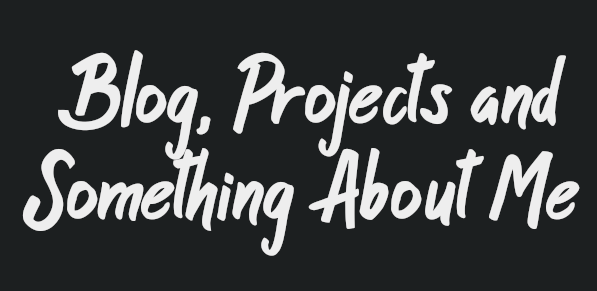
Çok araştırdım ama bulamadım. Gözünüze belki ilişebilir ya da kullanıyor olabilirsiniz. Paylaşırsanız sevinirim.
FONT BULUNMUŞTUR.
@BlancVier; hocamın belirttiği fonttur.
Creative Fabrica'nın Butter Pineapple fontu hocam
Spud Black İtalic fontu işinizi görebilir. Birkaç harfte değişiklikler var genel görünüm bire bir aynı gibi.
Creative Fabrica'nın Butter Pineapple fontu hocam
MilkyBrush-normal otf olabilir
- Benzerlik taşıyor ama neti lazım hocam. Yine de teşekkürler ekstra font her zaman iyidir.
- Hocam net font olarak @BlancVier; hocamın yazdığı font ile birebir. Yine de tavsiyeniz için teşekkürler.